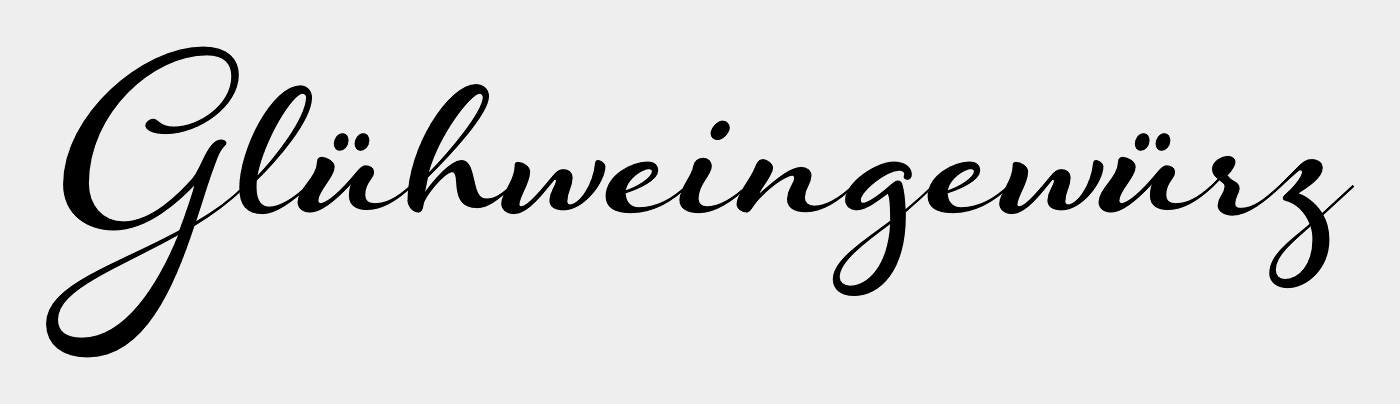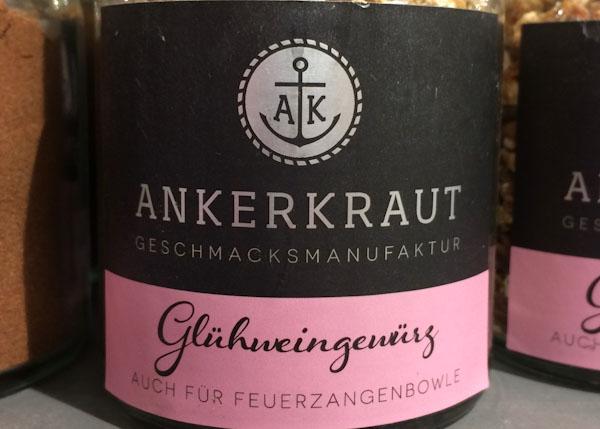
Heute im Edeka:
*ochmenno* Hätte ja gut werden können – von Laura Worthingtons Seite aus ist auf jeden Fall alles gut gewesen :-?:oops::cry:
Wobei hier Kerning/ Zurichtung auch komisch aussieht 🤔
Ich war mal wieder einkaufen ... 🤔
War das vielleicht mal WEISSWEIN Essig und man hat sich dann doch für Gemischtsatz entschieden :-?
Ist doch ganz einfach: das ist einfach ein Essig des Produzenten oder der Marke Weisswein. Der Eigenname unterliegt dann nicht den Rechtschreibregeln.
Dass es sich nicht um Weißweinessig handeln kann, dürfte wohl klar sein. :twisted:
Eine "Kühne" Schreibweise. Es ist eben Essig mit der Rechtschreibung auf Etiketten. Wer weiß, vielleicht ist auch nur Wein drin.
Oder einfach ein Schweizer Produkt... 🙄
Wir brauchen dringend höhere Einfuhrstrafzölle für Produkte mit ss statt ß!!!!!111elf%
Make ß great again!!!1
Kühne stammt aus Berlin und heute ihren Sitz in Hamburg.
Was ja nicht heißt, dass sie nicht auch für die Eidgenossen produzieren könnten.
Obwohl es dann wahrscheinlich »Wiesswienessik« oder so heißen müsste ...
und die Produktion in Hagenow
Gendermarketing aus dem Jahre 1869.
Uuii, in der Parallelstraße bin ich aufdgewwachsen.
Kühne-Essig wurde auch hier hergestellt. Ist aber schon 20 Jahre her, seitdem hat da niemand mehr sauber gemacht. Inzwischen ist die Fabrik abgerissen.
Wobei … sie hat ja buchstäblich recht. T is the (one) capital (letter) in (the word) Texas.
Solch eine Antwort könnte auch ein clever sarkastischer Kommentar zu der Unsinnigkeit solcher Fragen (Was sagen sie über die Bildung oder Intelligenz eines Menschen aus?) sein.
Nur ... Wie hat sie rausgehört, ob er
"What is the capital of Texas?",
"What is the capital of TEXAS?" oder
"WHAT IS THE CAPITAL OF TEXAS?"
gefragt hat? Evtl. wäre ja auch "X" richtig gewesen? ;-) Oder gar
"What is the largest capital of Texas?"
Tja, wenn nach dem Großbuchstaben gefragt wird (the capital), muss es sich logischerweise um eine Schreibweise mit nur einem handeln. Also die normale für Eigennamen.
Die ganze Geschichte ist natürlich ein Witz, den man auf (mindestens) zwei Arten interpretieren kann. Entweder ist es ein platter und sexistischer Blondinenwitz (dann ist Antwort »T« falsch und eben dumm, höhö) oder die clevere, junge Frau will genau diese Erwartungshaltung persiflieren, indem sie bewusst eine andere als die erwartete Antwort (für die man nicht schlau sein muss, sondern nur auswendig lernen) gibt, die aber (streng genommen) nicht falsch ist.
Ich glaube, so tiefsinnig hatte der Autor sich das nicht gedacht. Der "Intelligenzwettbewerb" innerhalb der hiesigen Schönheitswahlen ist hier immer ein beliebtes Hohnobjekt, besonders wenn sich ein Sternchen mal arg verhaspelt.
Buchstaben-Terror in der Hauptstadt … war heute sogar auf der Titelseite der B.Z. (»Wie Behörden Berlinern das Leben schwer machen«) …
Das finde ich sehr reißerisch. SI-Einheiten sind genormt, aus gutem Grund, und überhaupt nicht überraschend. Gut, der Zusammenhang ist klar, 1,5 KG am Brotregal meint weder anderthalb Kommanditgesellschaften noch 1,5 Kelvin mal Gauß, doch Regeln sind dafür da, Klarheit und Eindeutigkeiten zu präsentieren.
Würde eine Kommanditgesellschaft helfen? Dinkel oder Roggen?
P.S. Was passierte eigentlich, wenn ich mein Sortiment – aus rein stilistischen Erwägungen – in Kapitälchen setze? 1 kg Dinkelbrot … :-?
Habe nur versucht, im Tenor der Berichterstattung zu bleiben (… hätte vielleicht noch spezifischer im Aufschrei werden können: KLEINBUCHSTABEN-TERROR in der HAUPTSTADT!) Bin ansonsten ganz deiner Meinung  … lang lebe die Berliner »Behördenwillkür« (solange es mit dem Mietendeckel klappt) ;-)